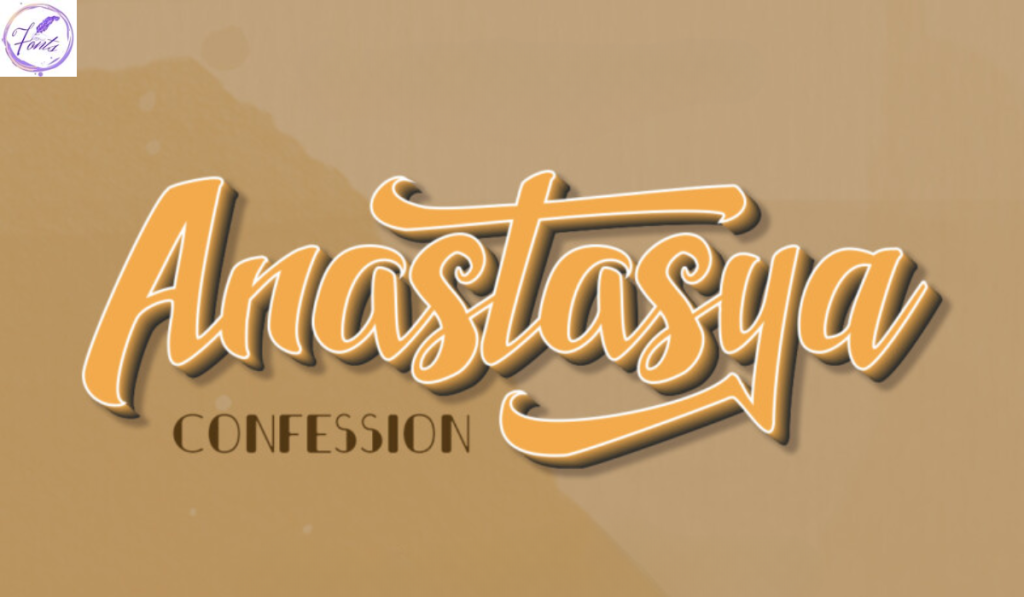
Font Anastasya Confession việt hóa
Tác giả: Rvq Typefoundry
Ngày phát hành: 2021
Ngôn ngữ: Tiếng Việt, Tiếng Anh, và nhiều ngôn ngữ khác
Bộ Font: Anastasya Confession
Phân loại: Cá tính, độc đáo, cổ điển, sang trọng
Kiểu chữ: Kiểu chữ viết tay
Font Anastasya Confession là một font chữ mang phong cách lãng mạn và tinh tế, được phát triển bởi nhà thiết kế nổi tiếng Rvq Typefoundry vào năm 2021. Với các đường nét uyển chuyển, mềm mại và đầy cảm xúc, font chữ này phù hợp cho các dự án sáng tạo như thiệp mời, tiêu đề, và các bài viết cần sự duyên dáng. Font Anastasya Confession nổi bật với sự cân bằng hoàn hảo giữa sự thanh lịch và hiện đại, giúp các thiết kế của bạn trở nên cuốn hút và đặc biệt hơn.
Đánh giá font anastasya confession
Font Anastasya Confession đã nhận được nhiều đánh giá tích cực từ cộng đồng thiết kế nhờ vào vẻ đẹp và tính linh hoạt của nó. Nhiều nhà thiết kế đánh giá cao khả năng tạo điểm nhấn cho các dự án của font chữ này. Đặc biệt, phiên bản Việt hóa của Font Anastasya Confession giúp người dùng Việt Nam dễ dàng sử dụng mà không gặp bất kỳ trở ngại nào. Với bộ ký tự đầy đủ và hỗ trợ đa ngôn ngữ, font chữ này là lựa chọn tuyệt vời cho những ai muốn thêm chút lãng mạn và tinh tế vào thiết kế của mình.